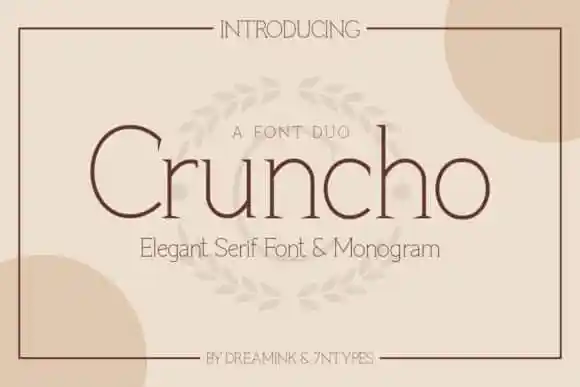
Cruncho Serif Font – Fonte Grátis
Cruncho Serif Font
A Cruncho Serif Font é uma elegante tipografia serifada que traz um toque de tecnologia e temas futuristas. Desenhada e compartilhada pelo designer 7NTypes, ela incorpora características sólidas e largas que combinam perfeitamente com um design moderno e clean. Seu estilo simples e limpo a torna uma fonte versátil, adequada para uma variedade de projetos gráficos – seja eletrônicos ou impressos. Cruncho tem o potencial de se tornar sua fonte preferida, independente do propósito da sua criação. Seja um logotipo, um design editorial ou até mesmo um site, essa fonte é uma escolha inteligente para qualquer projeto que busque elegância e sofisticação.